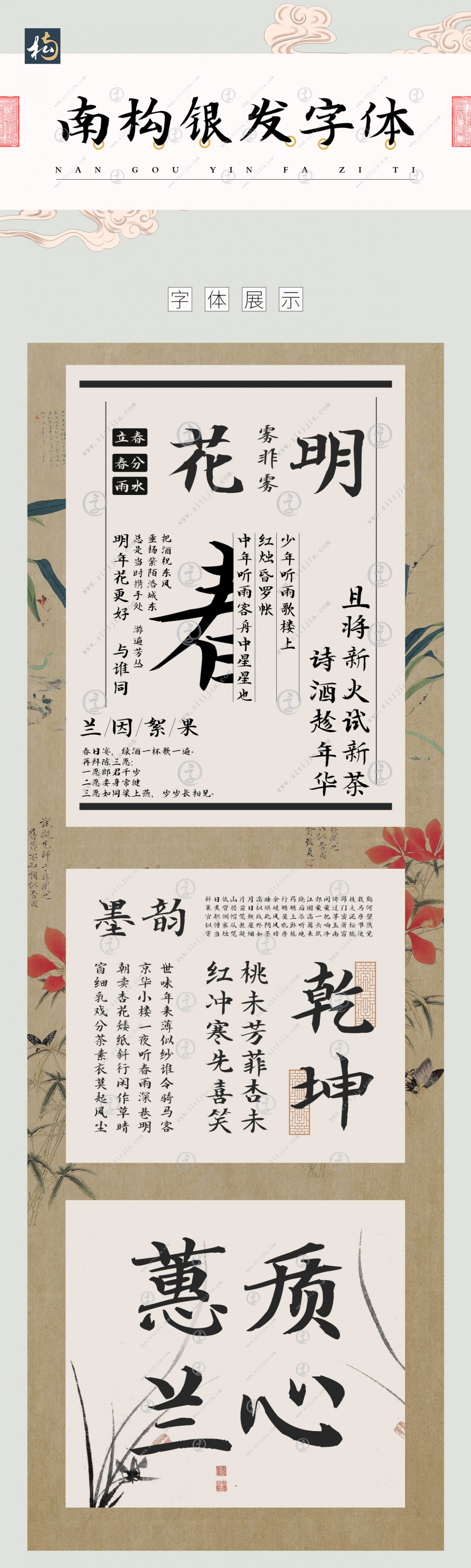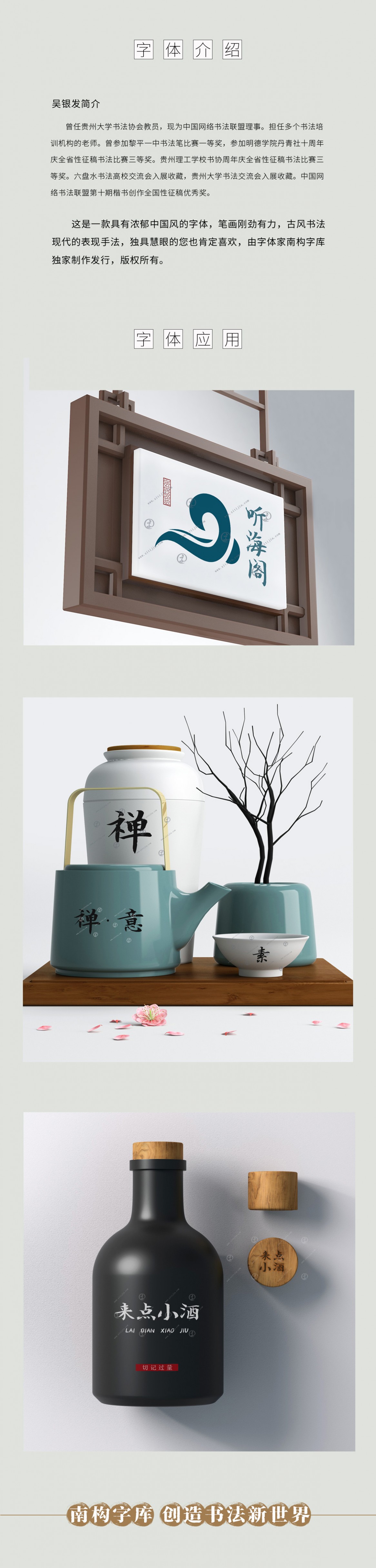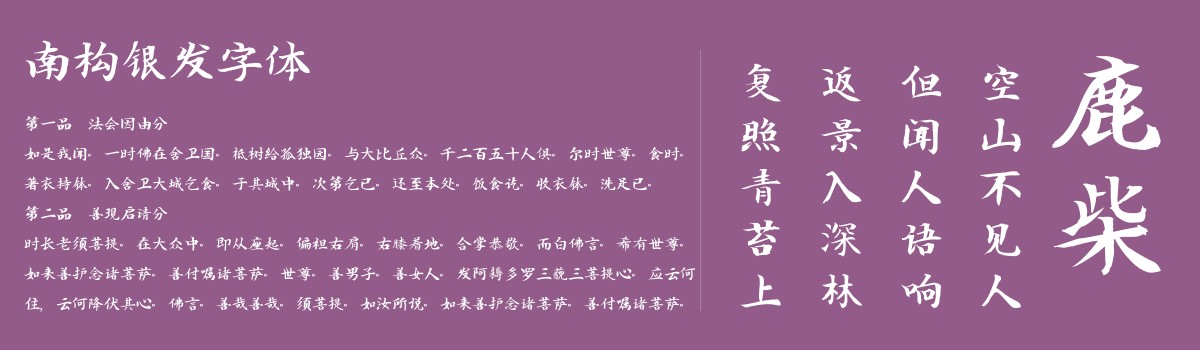
南构银发字体
这是一款具有浓郁中国风的字体,笔画刚劲有力,古风书法现代的表现手法,独具慧眼的您也肯定喜欢,由字体家南构字库独家制作发行,版权所有。
吴银发简介
曾任贵州大学书法协会教员,现为中国网络书法联盟理事。担任多个书法培训机构的老师。曾参加黎平一中书法笔比赛一等奖,参加明德学院丹青社十周年庆全省性征稿书法比赛三等奖。贵州理工学校书协周年庆全省性征稿书法比赛三等奖。六盘水书法高校交流会入展收藏,贵州大学书法交流会入展收藏。中国网络书法联盟第十期楷书创作全国性征稿优秀奖。